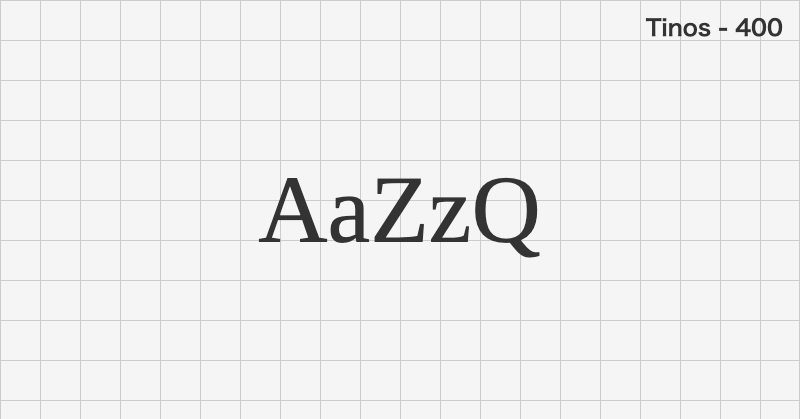
Tinos – 商用利用できる明朝体フリーフォント
Tinos 明朝体フォントの文字見本 (無料ダウンロード) 明朝体
Tinos は、セリフ体フォントで、特に印刷物やデジタルメディアにおいて高い可読性を提供します。実用性が重視されています。
ラテン文字、ラテン文字拡張、ベトナム語、キリル文字、キリル文字拡張、ギリシャ文字、ギリシャ文字拡張、ヘブライ語 に対応しており、国際化を前提としたデザインや文章表示に使えます。
ウェイトは 標準、太字、斜体 を収録しており、本文から見出しまで使い分けることができます。
Tinos は、Steve Matteson によって設計された実用性重視のセリフ体フォントです。Times New Roman™ と互換性のある幅設計を持ち、ドキュメントのプラットフォーム間での互換性を確保しています。印刷物、ウェブ、アプリなど幅広いメディアでの使用を想定して開発されています。
作者名 Steve Matteson